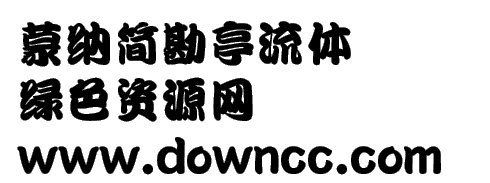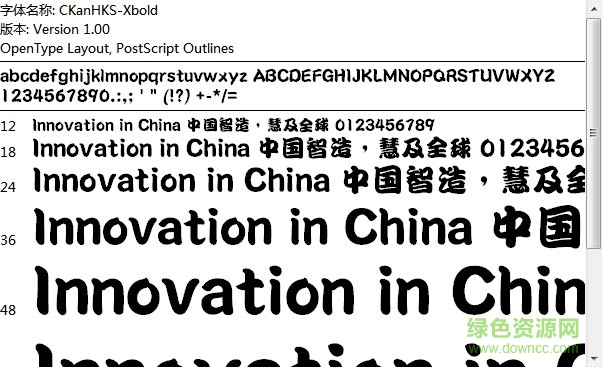
蒙納簡(jiǎn)勘亭流體是蒙納推出的一款勘亭流字體,是一款造型大方精簡(jiǎn)的日系字體,字跡風(fēng)格類似唐朝楷書和隸書,所以廣受大家喜歡,快來(lái)綠色資源網(wǎng)下載試試吧!
蒙納簡(jiǎn)勘亭流線條流暢而略顯組裝,字庫(kù)完整,整體效果非常出色,可應(yīng)用于雜志報(bào)刊、文學(xué)創(chuàng)作、平面廣告、印刷包裝等領(lǐng)域,使用時(shí)請(qǐng)選擇“CKanHKS-Xbold”即可!
勘亭流體屬于江戶文字,是一種江戶時(shí)代(大體相當(dāng)于我國(guó)明末清初那段時(shí)間)所使用的廣告字體。在江戶時(shí)代,勘亭流字體是使用于落語(yǔ)、歌舞伎等的招牌或節(jié)目表的字體。